Ya que tenemos un gran repertorio de tipografías entre las que escoger tanto en nuestra computadora como en web (por ejemplo publicadas en nuestro blog), dependiendo del mensaje que queramos transmitir y el medio sobre el que lo hagamos, vamos a ver una serie de efectos que aplicar a nuestras letras para que nuestros mensajes cobren un atractivo especial.
Quizás muchos no sean grandes fans de los efectos en las tipografías, pero hay que reconocer que dependiendo de para que estemos escribiendo, un buen efecto puede dotar a nuestro mensaje de un mayor atractivo. Una buena manera de usar estos efectos es bajo dos preceptos: la simplicidad y la buena combinación estilo de tipografía-estilo de efecto.
La Simplicidad
Pensar en la máxima de “menos es más”. Normalmente con el efecto que aplicamos a la tipografía, estamos cargando el mensaje, por lo que si vamos a usar mensajes con efectos es mejor realizarlos sobre fondos planos o imágenes con un gran desenfoque.
Además si ponemos las tipografías sobre un fondo desordenado o el que se incluyen demasiados colores y formas, los efectos aplicados a las tipografías no se van a entender con precisión y corremos el riesgo de que se emborrone el mensaje.
Combinación estilo de tipografía-estilo de efecto
Si aplicamos un efecto que concuerde con el mensaje y sobre todo con la tipografía a la que se lo estamos aplicando, puede hacer que se realce y se comprenda aun más el mensaje. Es muy importante que el efecto tenga el mismo estilo que la tipografía a la que se le aplica. De esta manera, es difícil que encaje un efecto “futurista” como una tipografía retro.
Cuando aplicamos un efecto normalmente lo hacemos porque queremos resaltar algo del texto al que se le aplica, darle incluso movimiento, por lo que vamos a hacer que todo el mensaje transmita la misma sensación.
5 Recursos gratuitos
Así una vez tenemos claros los dos preceptos que hemos de tener en cuenta para aplicar bien un efecto a la tipografía, compartimos 5 recursos de efectos. Todos son descargables de manera gratuita y su uso es tan sencillo como abrirlos en Photoshop y cambiar las palabras que traen por defecto por las nuestras. También se puede cambiar la tipografía por lo que no hay excusa para no usarlos, de hecho, en cada uno de ellos os hago alguna recomendación de tipografías de uso (con tipografías de las que ya hemos hablado).
“Authentic”o efecto
Un efecto increíble en el que se acentúa la sombra con una diferenciación entre la base y el cuerpo, dotando a nuestras tipografías de un efecto futurista. Es recomendable usar con tipografías serif en mayúsculas, puesto que así las sombras tienen las serifas para darles sombra.
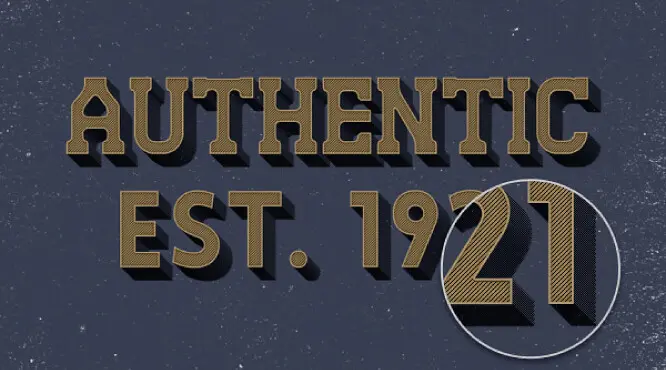
Efecto Nube
Es el efecto que más relieve da, de los de esta lista. Con él las palabras parecen que estén apoyadas sobre un tablero. Hacen recordar a los imanes con los que los niños forman palabras. Se puede usar tanto en mayúsculas como con minúsculas, pero en este caso, ya que el efecto aporta volumen e intensidad, es más conveniente que la tipografía sea serif y que tenga cierto grosor.
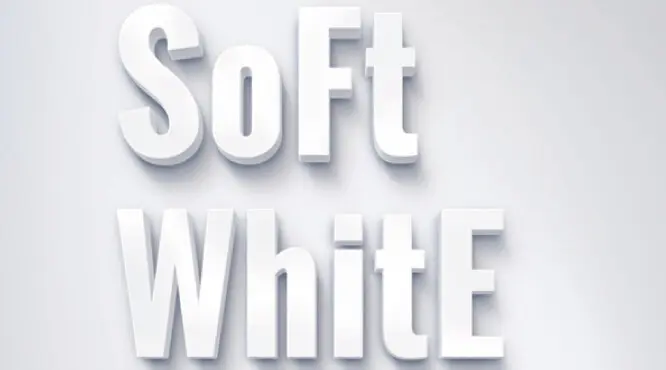
Sombras rayadas
Nos gusta este efecto porque combina a la perfección con gran numero de tipografías. Aconsejamos se use con tipografías en mayúsculas, pues en minúscula (aunque dependiendo de la tipografía que se use), tiende más a emborronar el mensaje.
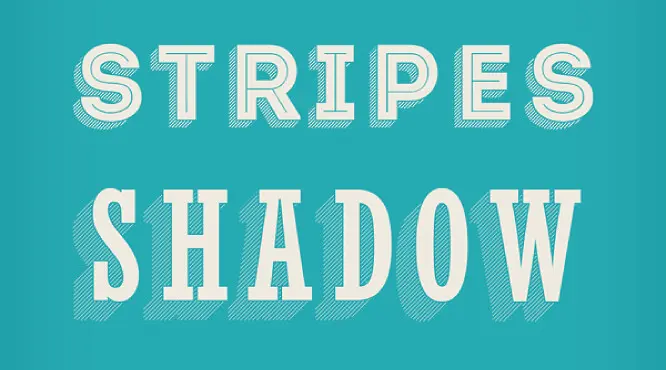
Retro
Este efecto retro es perfectamente combinable con tipografías en minúscula, aunque si tenemos una tipografía retro en mayúscula puede usarse también.
Úsala con Pacifico regular, Lobster two…
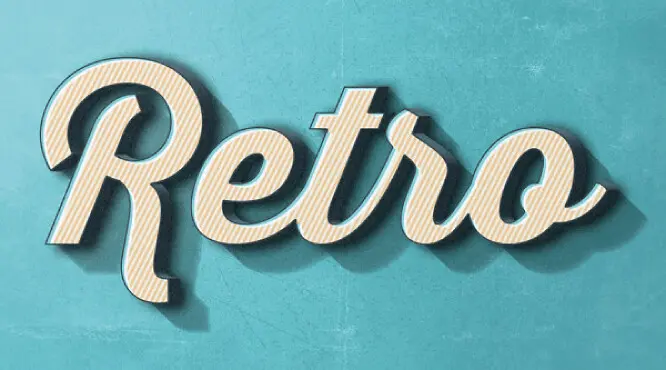
Efecto pizarra
Realmente uno de los efectos más usados, puesto que combina con mayor número de tipografías sin importar si esta en minúscula o mayúscula. Se puedes usar en tipografías con algún matiz retro, pero es perfectamente combinable con otras que no lo tienen.
Úsalo con Dan, Null, Kilogram, Bazar…
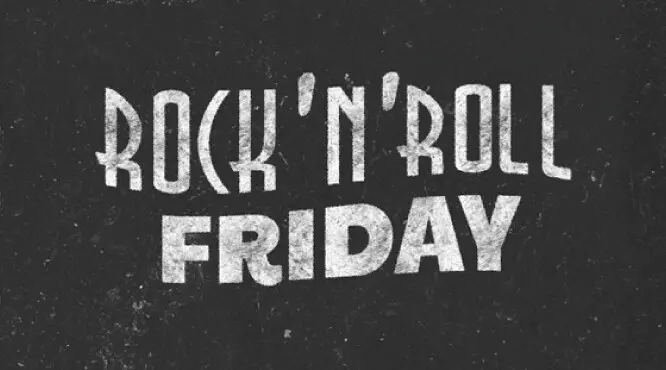
Efecto de texto holográfico
Nos complace compartir con usted un impresionante efecto de texto holográfico que le dará a sus textos y logotipos un aspecto futurista distintivo. Para aplicar este efecto a su texto, simplemente edite la capa inteligente y terminará en poco tiempo.
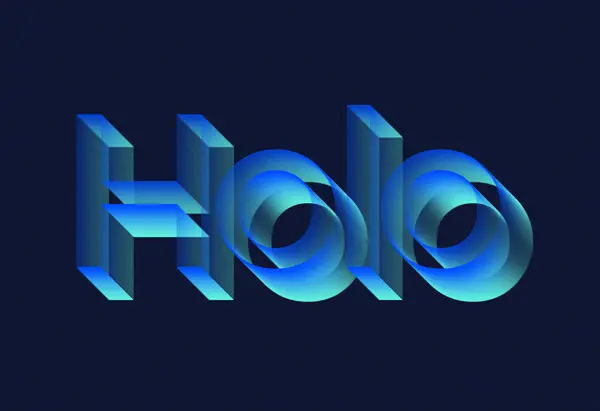
Efecto de texto regordete
Este efecto de texto de dibujos animados funcionará mejor con tipos de letra redondeados. Se crea a partir de una combinación de dos estilos de capa y es fácil de editar. La fuente utilizada es gratuita, puede encontrar el enlace de descarga en el archivo zip.
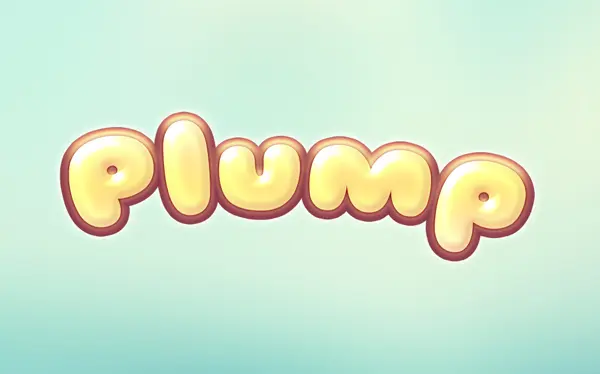
Efecto de texto Charlie
Se trata de un estilo retro en relieve, perfecto para titulares con aspecto antiguo. El texto se puede editar mediante un objeto inteligente, los colores se pueden cambiar y la fuente es gratuita. Qué más… ¡solo úsalo!
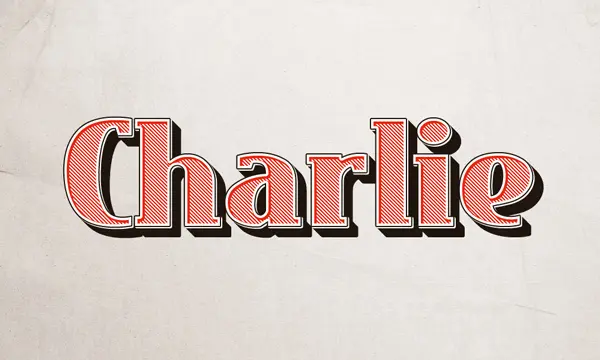
Efecto de tipografía retro de los 80
Crea una tipografía o logotipo icónico inspirado en los años 80 con este efecto de texto cromado. Para aplicar este efecto retro a su texto o forma vectorial, simplemente edite la capa inteligente y terminará en poco tiempo.